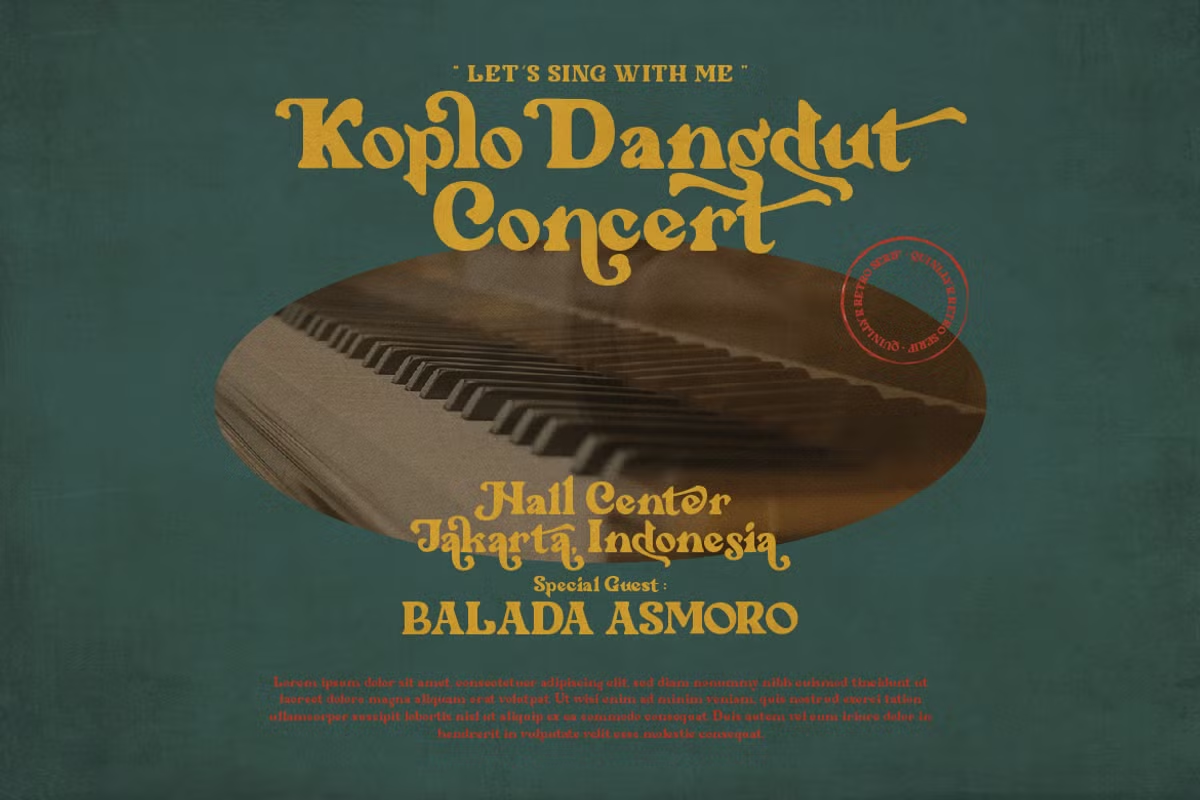
Quinlliyk Font
Description de Quinlliyk Font
Quinlliyk est une police qui a un look serif rétro plutôt audacieux. Les courbes épaisses du corps sont si audacieuses et me rappellent définitivement les années 60 et 70. Il a une empattement épaisse et un design incurvé qui lui ajoute plus d’unicité, bien sûr, pour tous vos produits. Cette police contient plus de 50 glyphes uniques et 10 ligatures uniques.
Quinlliyk convient à tout projet de marque, conceptions de logos, conceptions d’invitations de mariage, graphiques de médias sociaux, publicités, emballages de produits, conceptions de produits, étiquettes, photographies, filigranes et toute conception nécessitant une touche d’écriture manuscrite.
Des tonnes de glyphes
Ligature et suppléance